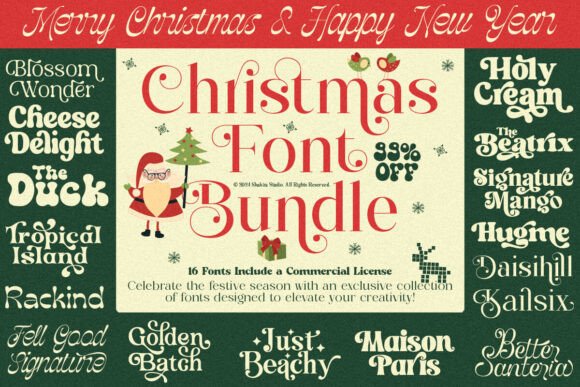
Christmas Bundle | Festive Holiday
Christmas Bundle | Festive Holiday – Avaliação Completa
Se você trabalha com design, artesanato ou produção de conteúdo visual, o Christmas Font Bundle | Festive Holiday chega como a solução definitiva para dar vida às suas criações natalinas. Este pacote reúne mais de 15 fontes premium, todas prontas para uso comercial, e foi cuidadosamente selecionado para atender desde projetos simples de cartões de convite até campanhas de branding de grande escala.
Por que este bundle se destaca?
- Variedade incomparável: de fontes cursivas elegantes como Fell Good Signature a tipografias divertidas como Cheese Delight, há uma opção para cada estilo de projeto.
- Design retro e festivo: a coleção traz um toque vintage que combina com o clima de fim de ano, mas também se adapta a projetos de primavera, verão e eventos temáticos.
Principais fontes do bundle
- Better Santeria – estilo manuscrito com traços ousados.
- Fell Good Signature – assinatura elegante, perfeita para convites de casamento.
- Blossom Wonder – delicada e floral, ideal para branding de beleza.
- Hugme – tipografia acolhedora, ótima para camisetas e merchandise.
- Rackind – robusta e moderna, funciona bem em logotipos corporativos.
- Kailsix – design clean, ideal para layouts de sites.
- Cheese Delight – divertida e descontraída, perfeita para festas infantis.
- Masion Paris – sofisticada, traz elegância a convites de gala.
- Signature Mango – cursiva leve, ótima para posts de mídia social.
- The Beatrix – clássica e refinada, versátil para revistas.
- Holy Cream – suave e cremosa, excelente para embalagens de alimentos.
- Aminah – toque oriental delicado, ótimo para projetos culturais.
- The Duck – divertida e única, perfeita para designs lúdicos.
- Golden Batch – estilo dourado e luxuoso, ideal para campanhas premium.
- Just Beachy – vibe praiana, combina bem com verão e férias.